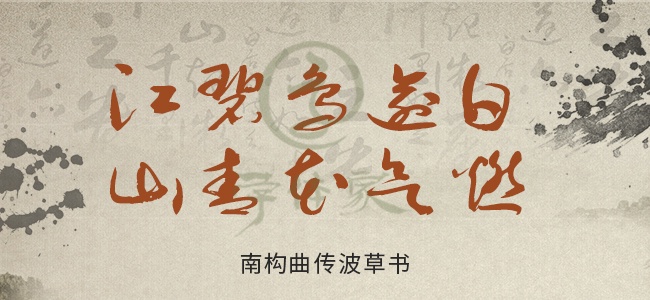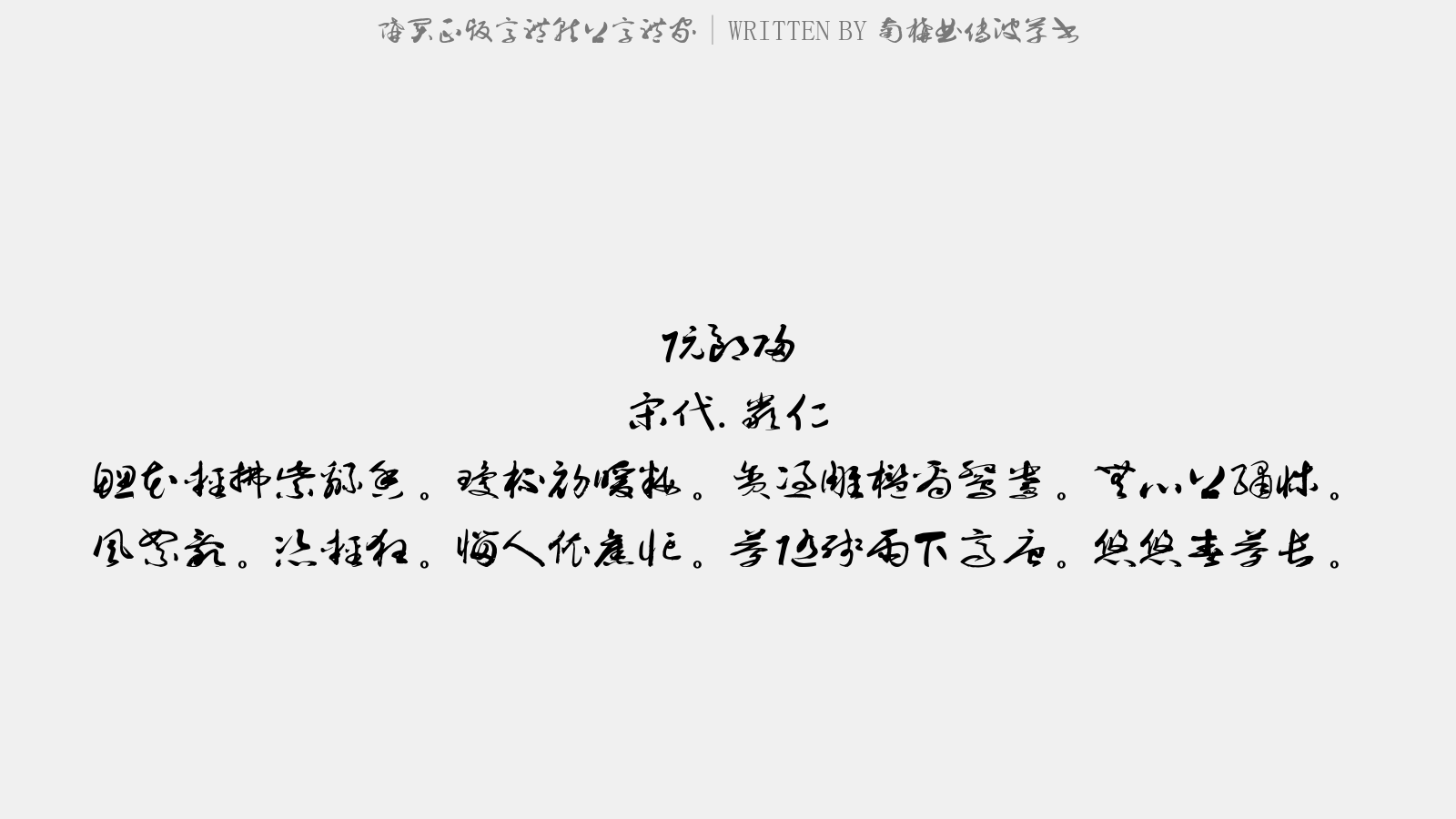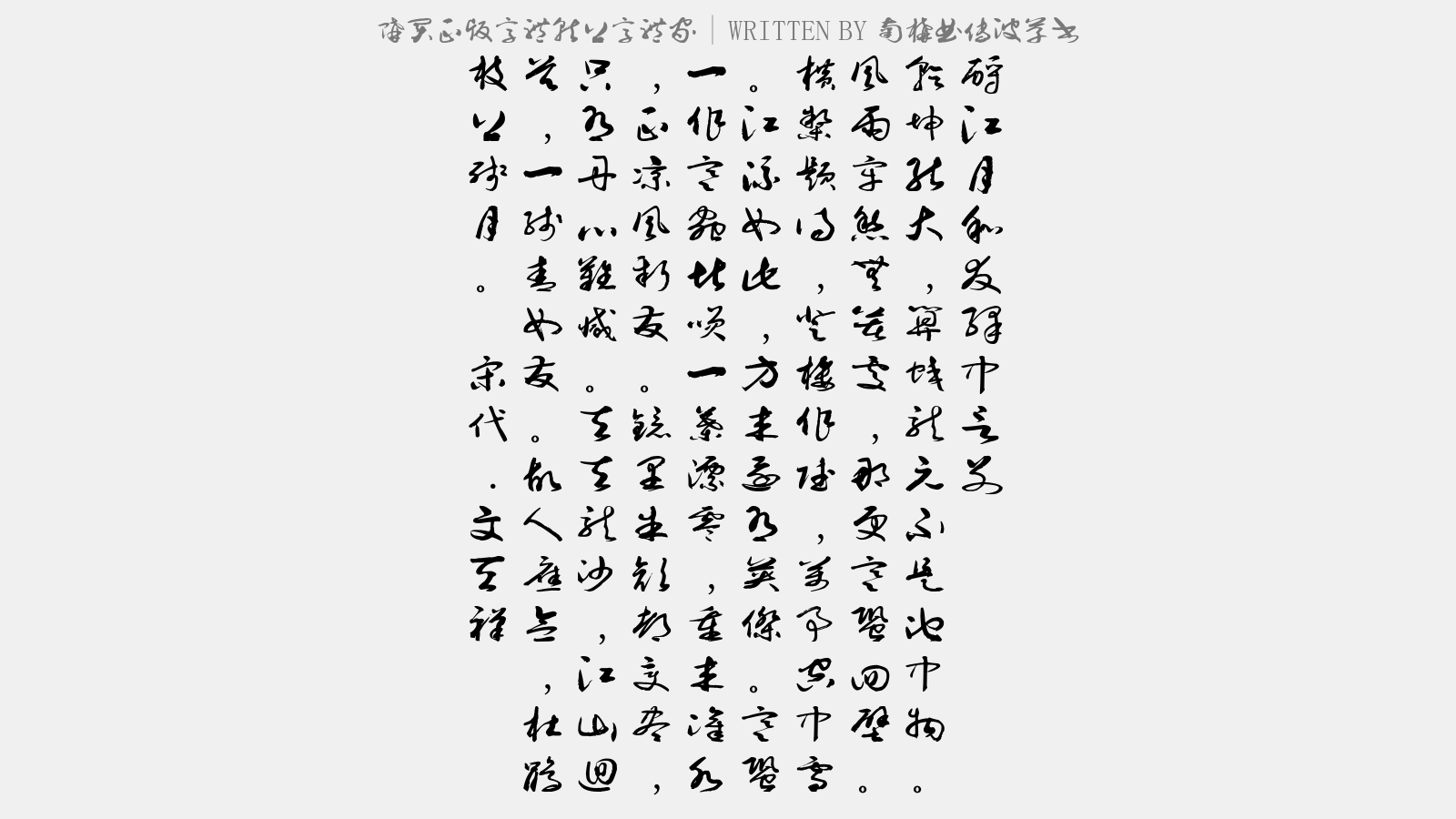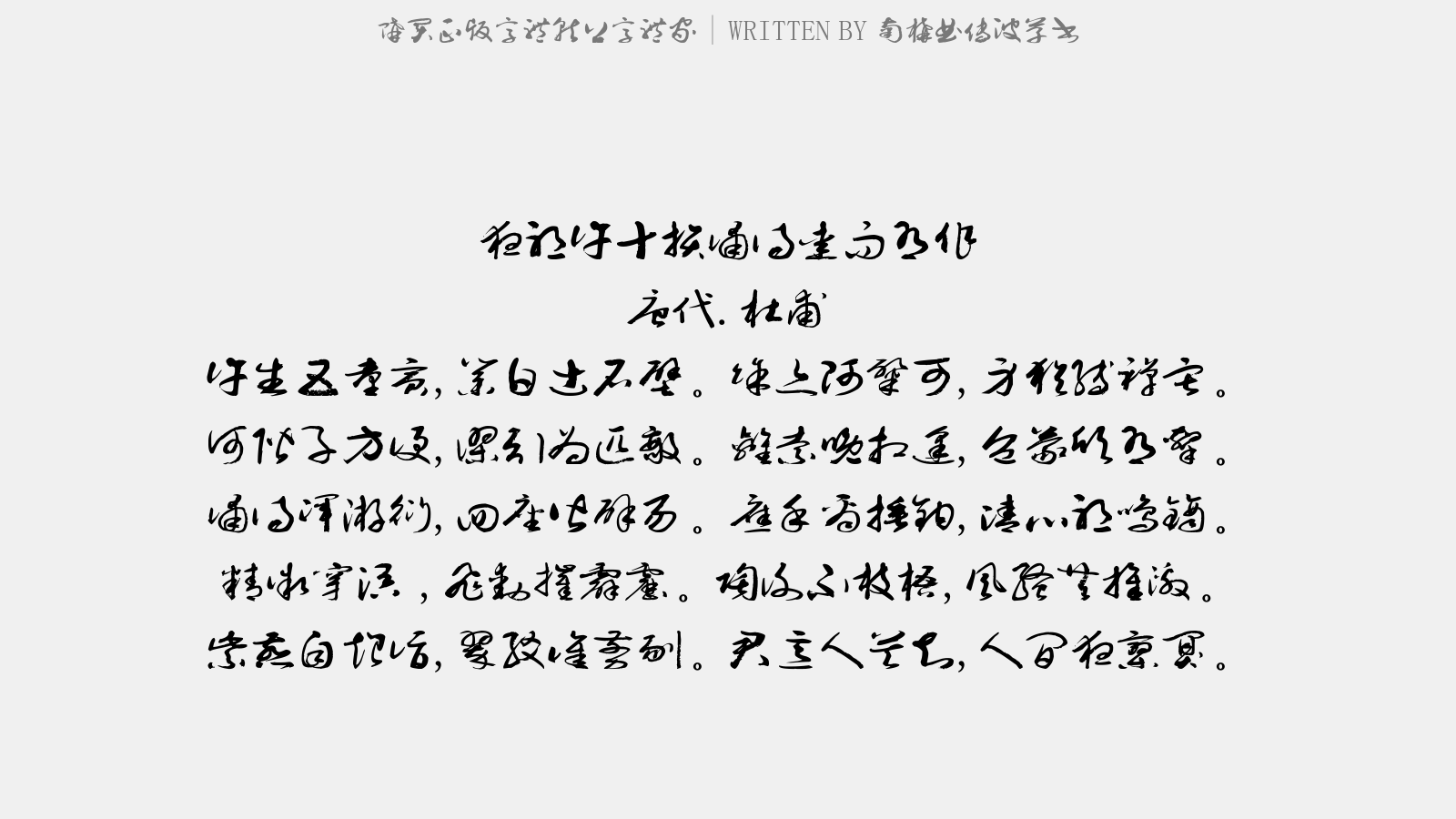
南构曲传波草书
字体作者:曲传波
字体名称:南构曲传波草书
字体家族:南构系列
书体类型:手写体
字体公司:南构字库
字体设计:南构签约设计师
南构曲传波草书
这款南构曲传波草书字体,是由书法家曲传波老师书写的草书字体,在南构字库家族中,草书字体还是不多的,这款是众多草书字体中较优秀的一款,特别推荐给朋友们,这款字体如果用在标语海报,产品包装,广告招牌上都是非常不错的选择,由字体家平台南构字库独家制作发行,现在已经发布个人版和正版在线购买业务,购买正版字体,就上字体家!
这款草书字体非常乙肝,就是感觉没有草书的神态,可能草书出的字库就是不太好看吧